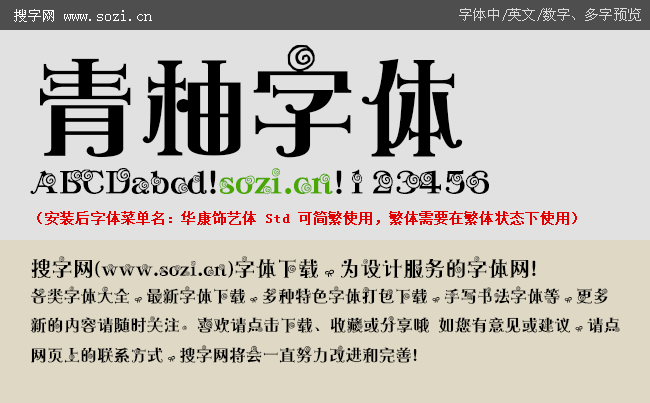
青柚字體
搜字網(wǎng)給大家提供一款青柚字體手機中文字體下載。這款手機字體是以華康飾藝體為原形,將個別的筆畫變成了可愛的卡通花紋。華康飾藝體是一款帶有西方古典美的字體,橫細豎粗,起筆落筆處加有西方特色的櫬線裝飾,跟西方的花體字很類似。加入了卡通圖案后更增添了趣味性,特別適合喜歡手機字體個性一些的朋友在手機上安裝使用。